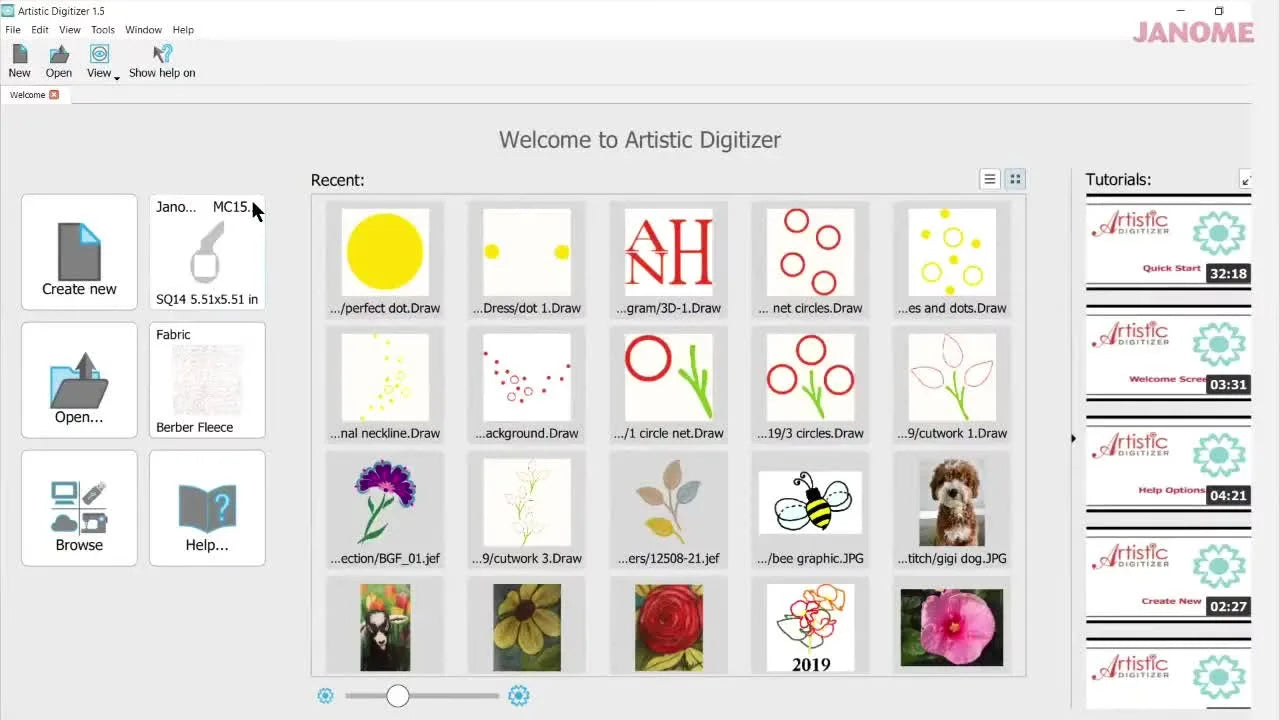
1 Contesto e quando usarlo
L’effetto 3D in ricamo a macchina è il risultato di più passaggi di sottostruttura che accumulano filo sotto i punti Satin. Il rialzo non è un filtro grafico: è costruzione fisica dello strato di punti, visibile e percepibile al tatto. Questo approccio offre una presenza forte su iniziali, loghi e monogrammi.
1.1 Che cos’è l’underlay 3D
In Artistic Digitizer l’underlay 3D (varianti 1D–5D) definisce quante “passate” preparatorie vanno sotto il riempimento Satin. Con 1D avrai meno passaggi di preparazione; con 5D la densità cresce sensibilmente e il rilievo è più marcato. In pratica, il software fa eseguire alla macchina più corse avanti e indietro prima di passare alla sezione successiva del disegno.
1.2 Perché le foto non bastano
Guardando l’esempio di profilo si intuisce la differenza di spessore, ma è la vista di taglio a dare consapevolezza del rilievo. Le immagini non rendono la sensazione tattile del punto accumulato; per questo i test su campione restano decisivi.
1.3 Quando scegliere il 3D
- Monogrammi centrali su biancheria o regali personalizzati.
- Iniziali singole su quadretti o cornici decorative.
- Elementi tipografici di dimensioni medio-grandi dove il Satin può esprimersi senza rischiare di impigliarsi.
1.4 Attenzione alle dimensioni del Satin
Il rilievo spinge a “ingrassare” le lettere. Tuttavia, Satin eccessivamente largo può impigliarsi su accessori o abiti. La creatrice del tutorial sottolinea di valutare sempre la larghezza delle barrette Satin e la crescita di spessore data dal 3D.
2 Preparazione
Prima di metterti al lavoro, definisci l’obiettivo (monogramma o lettera singola) e organizza ambiente e file.
2.1 Requisiti minimi
- Familiarità di base con l’interfaccia: pannello Proprietà, finestra Sequenza, strumenti di Lettering/Monogram.
- Tessuto e filati per i test di cucitura futuri.
2.2 Nota sulle famiglie di font
Nel software troverai font pre-digitalizzati (XPG) e font TrueType presi dal tuo computer. I font pre-digitalizzati sono spesso più prevedibili su Satin e underlay 3D, perché ottimizzati per il ricamo.
2.3 Strumenti e accessori sul banco
Checklist Preparazione
- Artistic Digitizer aperto e funzionante.
- Scelta preliminare: Monogram o Text (lettera singola).
- Campioni di tessuto disponibili per i test.
- Consapevolezza delle differenze tra font XPG e TrueType.
3 Impostazione
Impostare correttamente il progetto in Artistic Digitizer ti evita correzioni a valle.
3.1 Avviare un nuovo monogramma
- Clicca Create New.
- Vai su Lettering, poi Monogram.
- Inserisci il testo (per esempio due iniziali) e seleziona il Template desiderato (nel video viene apprezzato il Template 15 per il suo aspetto moderno).
3.2 Scelta del font e del layout
- Trova il font dal menu a tendina: i font XPG sono pre-digitalizzati; i TrueType vengono digitalizzati al volo dal software.
- Conferma con OK per far comparire il monogramma in area di lavoro.
- Imposta dimensioni ragionevoli (nell’esempio, 4,00 × 4,00 pollici per altezza/larghezza), tenendo a mente la cautela sui punti Satin larghi.
3.3 Perché Satin e non Step Fill
I riempimenti Step non sovrappongono le passate come il Satin; per creare rilievo, il Satin è indispensabile. Il 3D nasce proprio dalla combinazione Satin + underlay multiplo.
Controllo rapido
- Il monogramma è visibile in area di lavoro con il font scelto.
- Il pannello Proprietà mostra la possibilità di selezionare il tipo di riempimento.
4 Esecuzione dei passaggi
In questa sezione convertiamo il disegno in Satin e applichiamo i diversi underlay 3D, verificando la resa con Slow Redraw.
4.1 Convertire in Satin e attivare l’underlay
1) Seleziona il monogramma nella finestra Sequenza. 2) Nel pannello Proprietà, cambia Fill in Satin. 3) Spunta Underlay e apri le opzioni per scegliere la variante 3D (1D, 3D, 5D, ecc.).
Consiglio pro Prima di scegliere definitivamente l’underlay, pianifica due simulazioni rapide con Slow Redraw: una con 1D per capire il minimo rilievo, una con 5D per vedere il massimo. Questo confronto visivo ti guida a una decisione informata.
4.2 Provare l’underlay 1D e poi 5D
- Con 3D-1 vedrai poche passate avanti/indietro per sezione: rilievo contenuto e cucitura più snella.
- Passando a 3D-5 la simulazione mostra molte più passate e un accumulo evidente di filo.
Attenzione Quando aumenti la densità (es. 5D), ricordati che cresce anche lo spessore: in macchina dovrai alzare il piedino per non farlo “cavalcare” il ricamo, cosa che potrebbe allentare la tensione e sporcare la qualità del punto.
- Simula con Slow Redraw e confronta le varianti.
- Alza l’altezza del piedino in macchina prima di cucire rilievi importanti.
- Esegui test su campione per scegliere la densità più adatta.